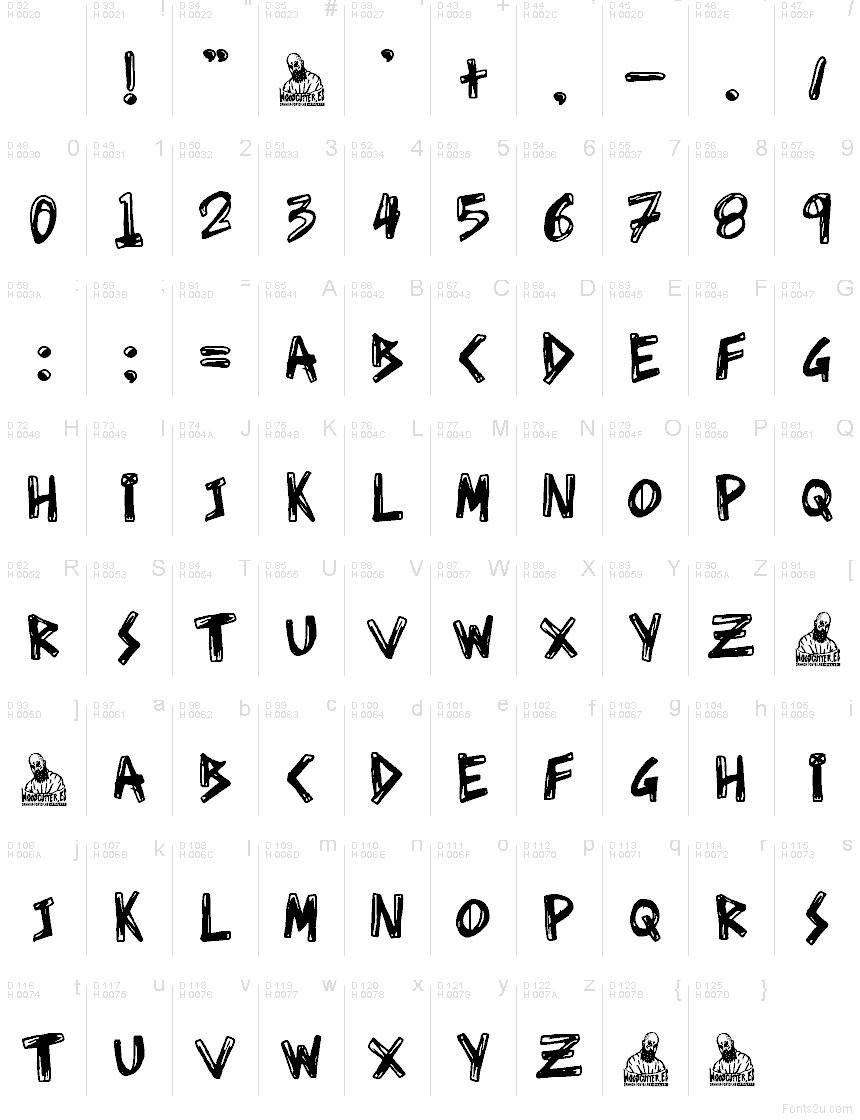
Barcelona Nacional od Woodcuttera to darmowy, ręcznie wycinany krój pisma typu display, emanujący surową energią plakatów ulicznych. Litery wyglądają, jakby zostały wyrzeźbione w odpadach drewna lub namalowane na znalezionych deskach – mają masywne, nieregularne kreski, przycięte rogi i drobne, „odbite” detale, które sprawiają, że zestaw wydaje się surowy i swojski, a nie dopracowany w każdym calu.
Świetnie sprawdzi się na ulotkach koncertowych, w brandingu barów, na plakatach festiwalowych, okładkach zinów czy tytułach, gdzie darmowy krój z takim ręcznie wykonanym pazurem może nadać ton całej pracy. Ponieważ wielkie litery są szerokie, mocne i nieco niepokorne, najlepiej sprawdzają się w krótkich nagłówkach, hasłach na okładki czy logotypach, w których ta „ciosana” faktura gra pierwsze skrzypce.